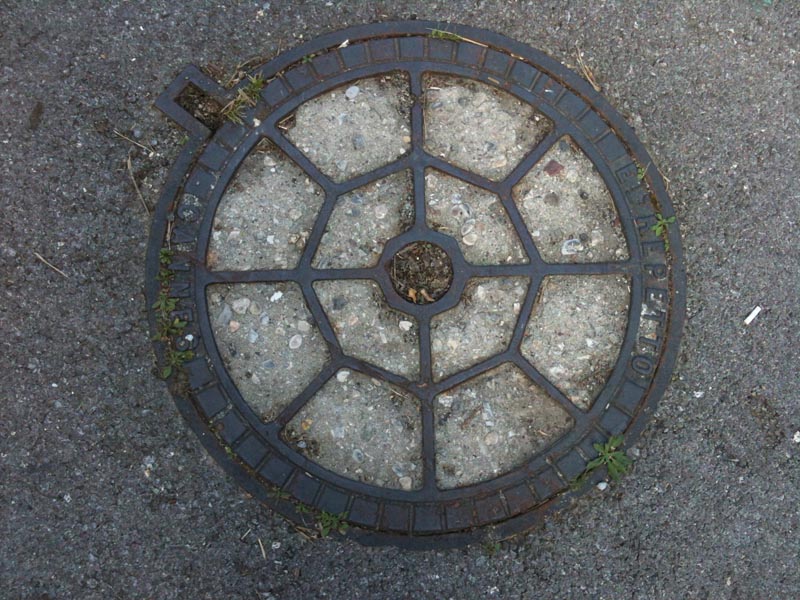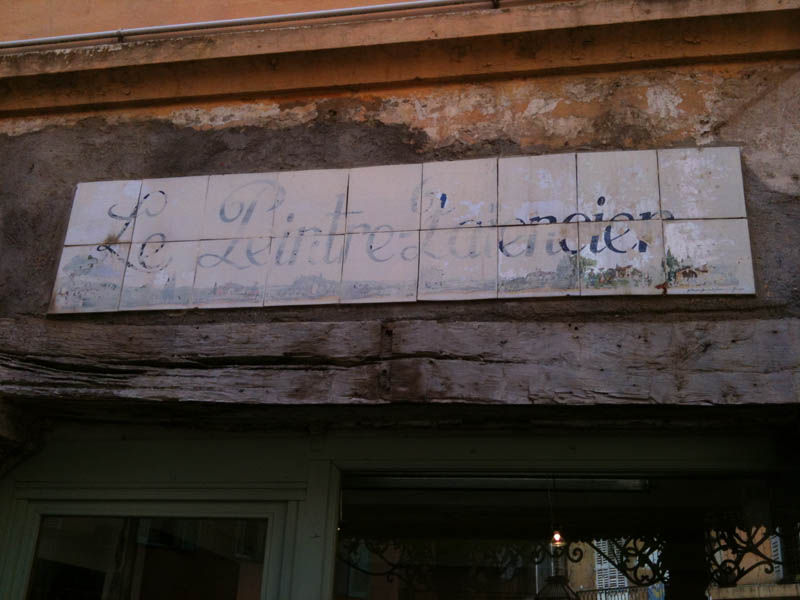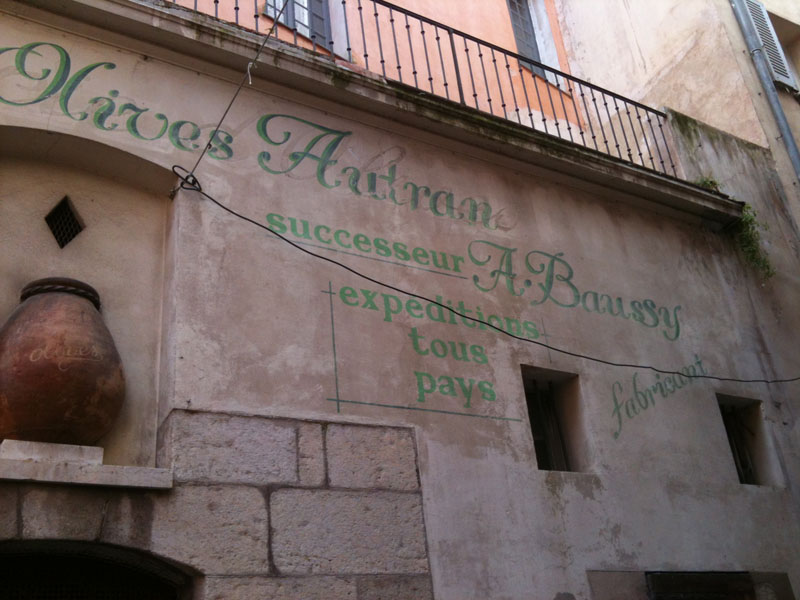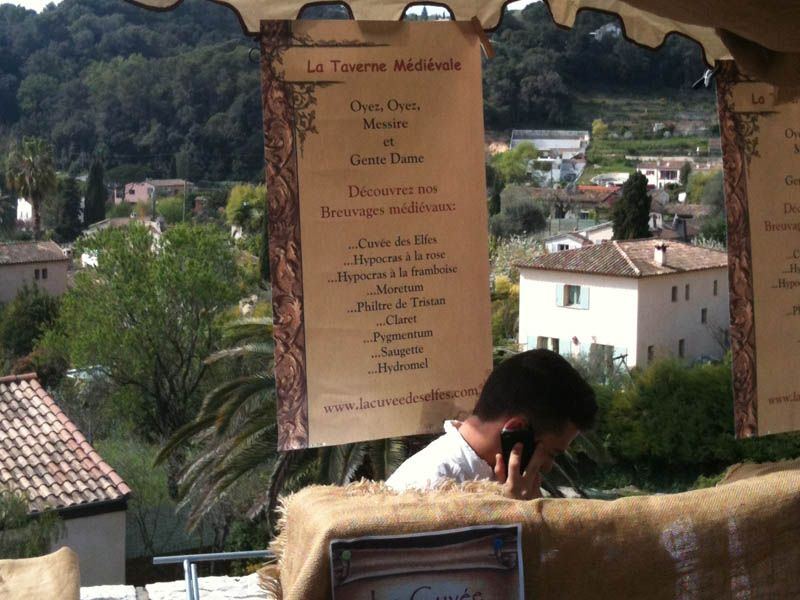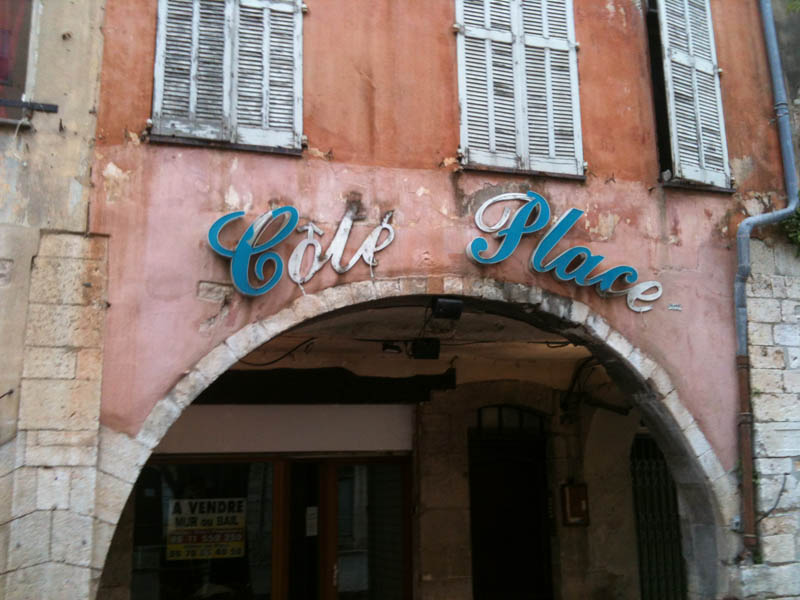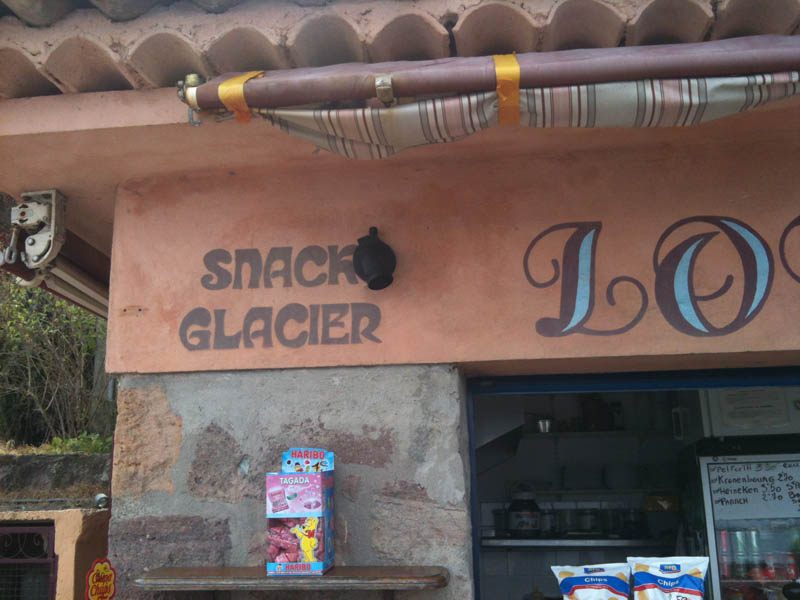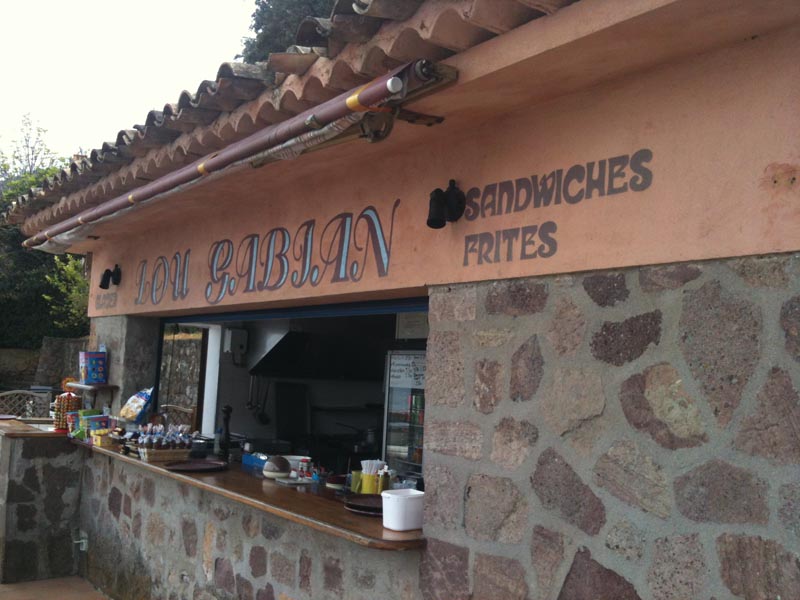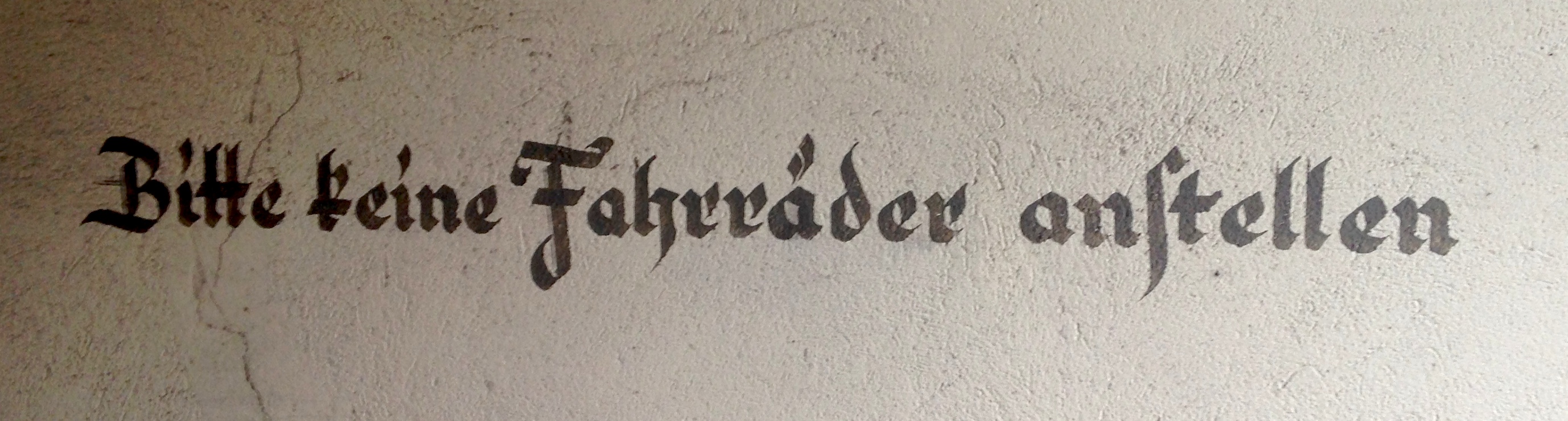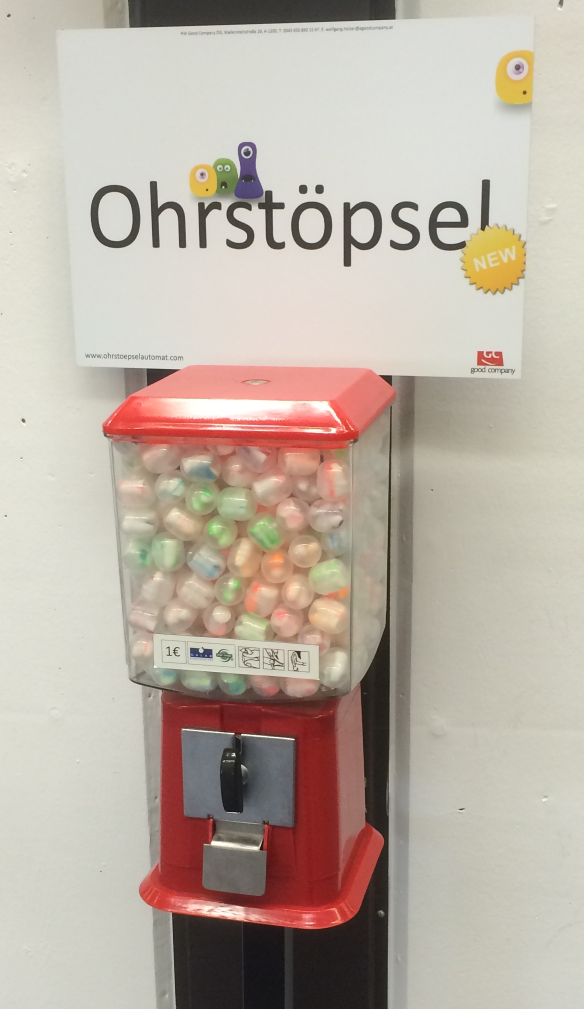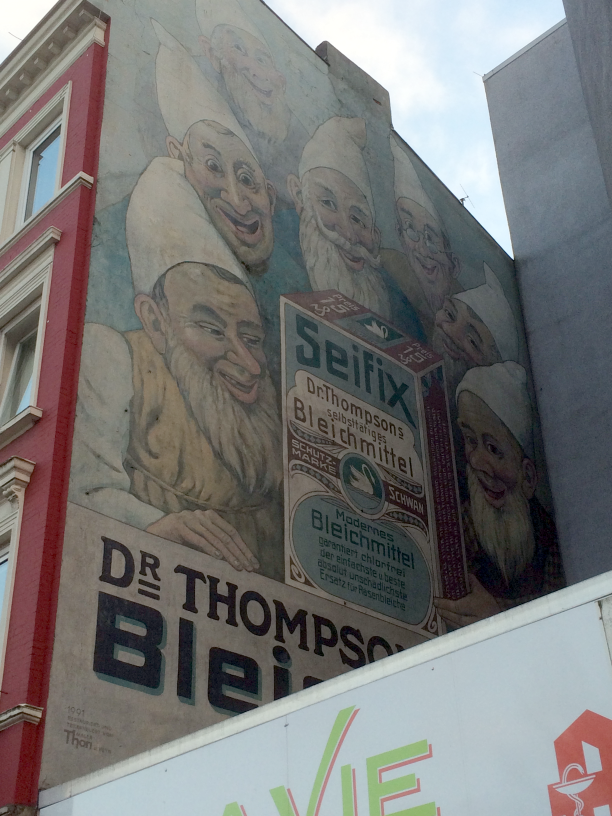
Typostreifzug durch die Stadt ...
ein für wiener verhältnisse relativ ungewöhnliches straßenschild mit gebrochenen lettern.
die auf blauem email sind ja sonst fast immer in dieser klassischen wiener schrift, die vor einiger zeit als henriette digital herauskam
Hier ein paar Mitbringsel von einer Woche Urlaub im
(Cannes, Grasse, Nizza, Antibes und umzu)
Schilder und Ghost Signs
Kuriosa
Mittelalterliche Comic Sans – und bei den Flaschen haben sie sich solche Mühe gegeben:
Kerning? wozu ..?
Apostroph oder Akzent?
Der Klassiker: Hauptsache irgendwo sind Pünktchen!
Diverses
Eins für die Illustratoren:
... und ein Gullideckel:
Heute war ich mal unterwegs und habe was lustiges gefunden: jpkmxh.png
Es gibt sie also heute noch, diese tollen Automaten. Und für die Staatsbibliothek auch mal sinnvoll gefüllt...
Ferner sind mir folgende Dinge ins Auge gefallen, die ich Euch nicht vorenthalten möchte:
Ein restaurierte Wandgemälde:
Und bevor es verschwindet, ein "uralter" Firmenschriftzug:
Dieser schöne Kaffeklatsch hier war mir irgendwie bisher entgangen … hm.
Dann geb ich mal eine Visitenkarte mit einem (vermutlich einigen bekannten) Leipziger Klassiker:
Bei dem Wandgemälde erinnere ich mich noch an den Abriss des Hauses, dass dieses Reklamebild zum Vorschein kam. Schade, ich hätte damals das noch nicht übermalte Original fotografieren sollen :-( denn ich fand es farblich eigentlich viel schöner.
Rüegg:
Fast vergessen, ich habe ja Bilder aus Dänemark mitgebracht!
Das Bild stammt übrigens vom Strand in Lönstrup. Die haben da große schwere Eisenplatten auf den Sand gelegt, damit sie mit schwerem Baugerät nicht einsinken. Die Eisenplatten sind durch eingeschnittene Buchstaben »gebranded« und einige davon habe ich abgelichtet, weil sie so schön aussehen.
Hoheluft und Eppendorf. Und Uni. Das Wandgemälde kenne ich leider nur im restaurierten Zustand, soll ich demnächst mal mit einer richtigen Kamera da für Dich vorbeigehen?
Rüegg hat oder hatte wohl eine Verwaltung oder sowas in der Isestraße und das gefühlt seit ewig (dh. solange ich mich zurückerinnern kann). Aber da steht jetzt ein "Zu Vermieten"-Schild davor, da musste ich dann noch mal schnell das Iphone zücken.
Heute auf dem Weg im Lehmweg, fast an der Ecke zum Eppendorfer Baum, zwei "neue" Beschriftungen entdeckt die beim Renovieren freigelegt wurden:
und
Lustigerweise kannte ich noch beide Geschäfte, als sie noch in Betrieb waren -- zwischenzeitlich waren da noch andere Läden drin. Immer häufiger merke ich, wie alt ich bin. Für Radio Mellek (oder so ähnlich, Catfonts wird den Laden wohl auch kennen) hatte ich sogar noch Prospekte ausgetragen. Letzt hab ich mir sogar meine erste Jazz-CD gekauft!
Du hast mich mit diesem Thread dazu inspiriert, häufiger die Augen offen zu halten :) So werde ich allmählich zum Conservativen (im Wortsinne) :D
Es ist einfach zu schade, dass diese alten Anzeigen einfach übertüncht werden. Bei der Apostelkirche gibt es einen Hochbunker, bei dem sie im Zuge einer Wohngeschoßerweiterung auf dem Bunker die Fassade gereinigt haben. Die war bis untern Rand voll mit Anzeigen für Fleischereien, Umzugsunternehmen, Lagerräumen, Seifen, ... Damals fand ich das ärgerlich und heute ärgere ich mich, dass ich das nicht dokumentiert hatte.
Ich habe auch noch ein neues Bild, das stammt aus Bahrenfeld: